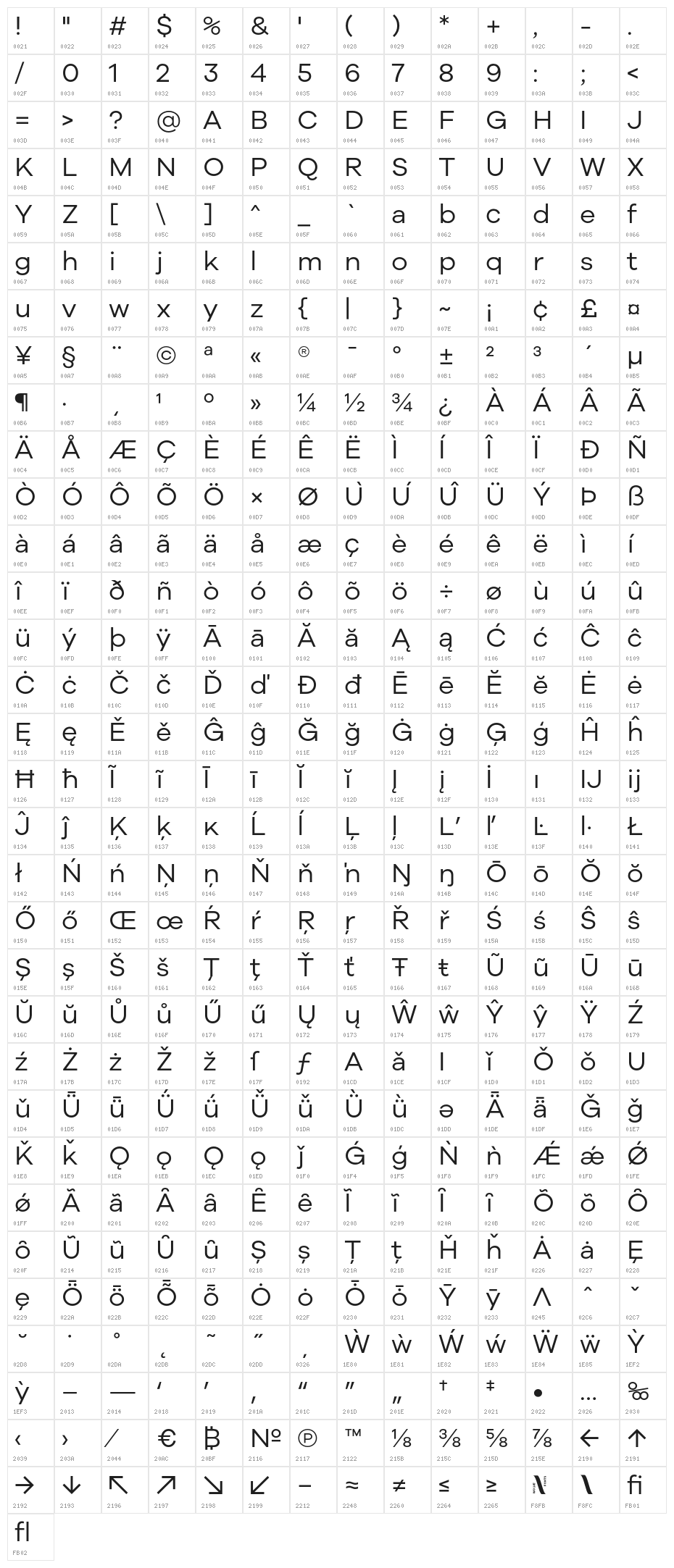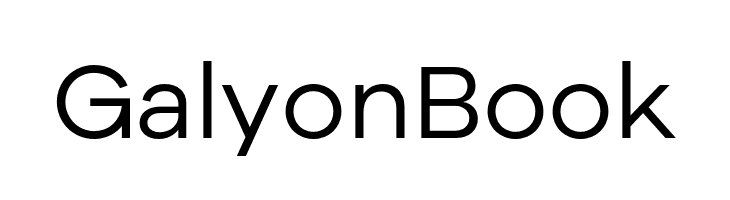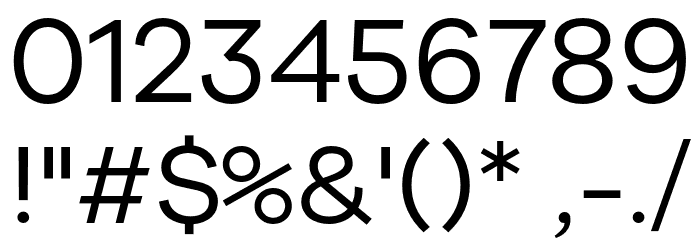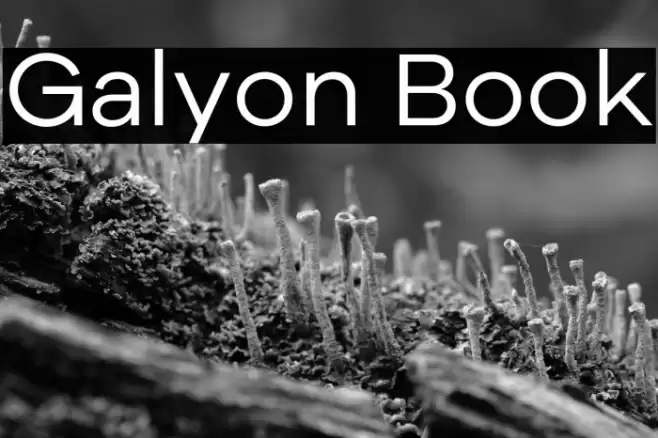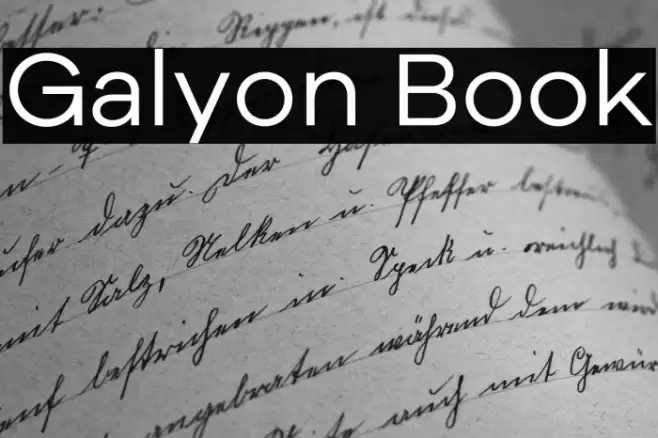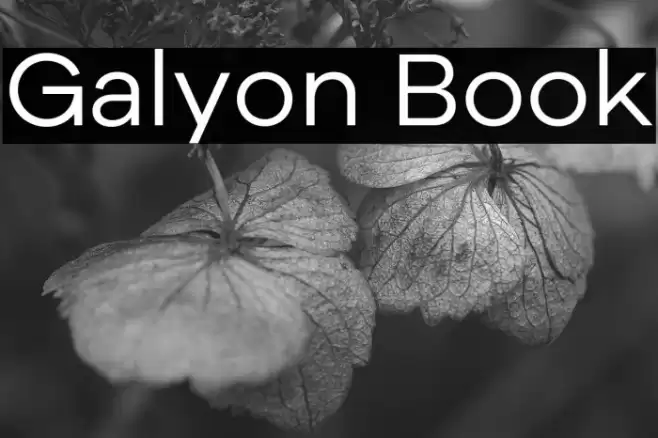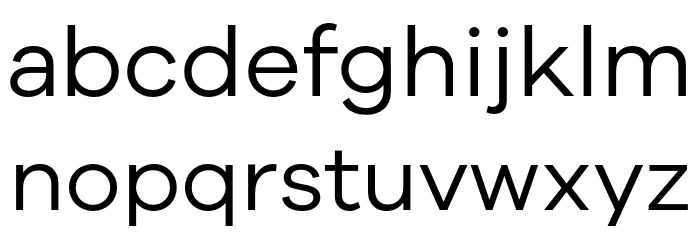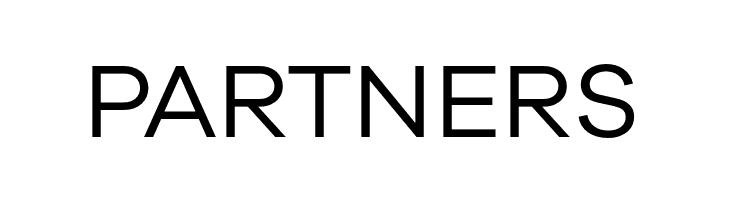
Galyon Book Font
| Anwendungsfall | Headlines, Body text, Logos |
| Vorgeschlagene Projekte | Ideal for digital interfaces, corporate branding, and editorial design due to its clarity and modern appeal. |